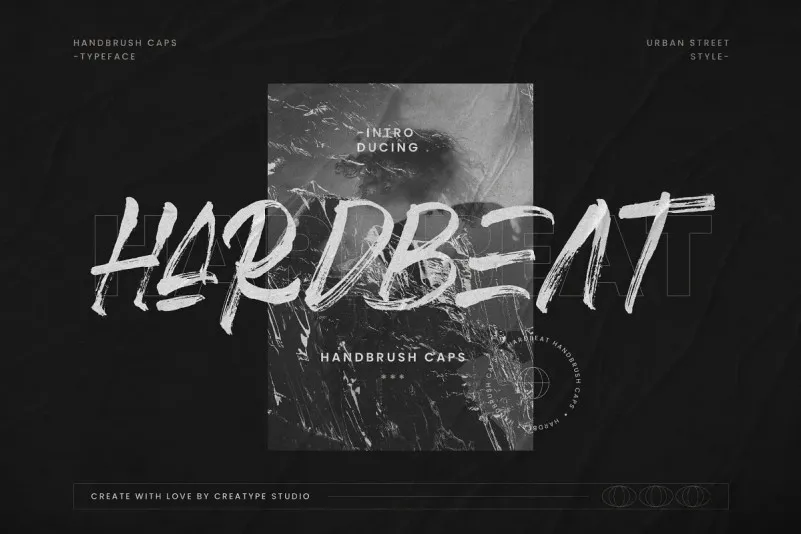
Hardbeat Font – Download Grátis
Esta fonte é perfeitamente projetada para atender a uma variedade de necessidades criativas na era digital. Com sua escrita rápida e elaborada manualmente com um pincel, oferece uma forte contraste entre curvas grossas e finas, proporcionando um toque autêntico que se assemelha à escrita à mão real. É perfeita para projetos de marca, logotipos, designs de casamentos, posts nas redes sociais, anúncios, embalagens de produtos, desenhos de produtos, rótulos, fotografias, marcas d’água, convites e até mesmo cartões de papelaria. Esta fonte também se destaca para qualquer projeto que exija um gosto por escrita à mão, tornando-a uma opção versátil e indispensável no seu arsenal de ferramentas de design.